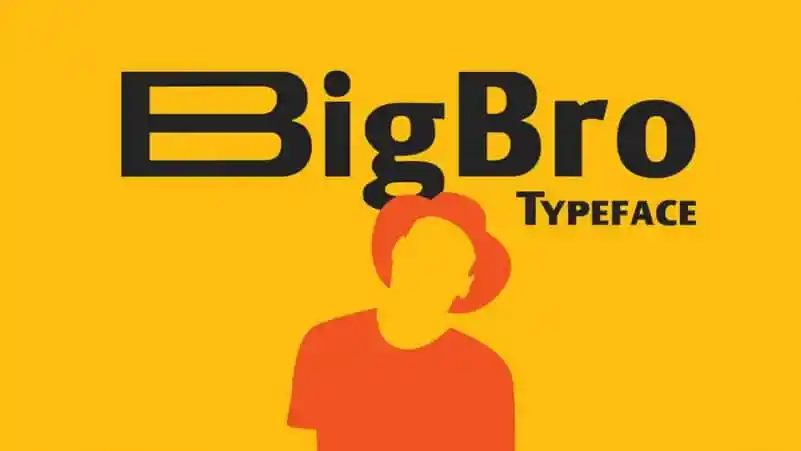
Big Bro Sans Serif Font é uma fonte sans-serif futurista e moderna que oferece uma sensação equilibrada tanto dos caracteres maiúsculos quanto dos minúsculos, criando um visual incrível. Com alternativas de letra maiúsculas estilizadas com design mais amplo, ela destaca os símbolos do título, dando-lhes um aspecto único e atraente. A fonte é projetada pelo designer Tapiwanashe Sebastian Garikayi e está disponível gratuitamente para uso sem restrições de royalties, incluindo suporte para múltiplas línguas. Sujeitosa, ela se destaca perfeitamente como opção ideal para headlines, posteres, banners e outras obras artísticas em sua versão sans serif.